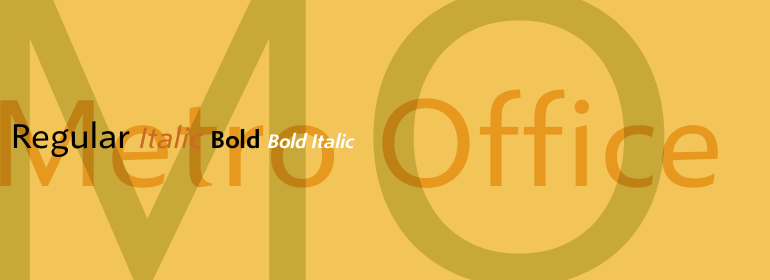
Metro® Office
Metro® Office,这款字体结构工整、笔画清晰,兼顾美观与易读性,适用于标题、正文、海报、包装、LOGO 等多种场景。字形优雅稳定,风格百搭耐看,适配日常排版与创意设计,让文字呈现更舒适、更具质感。Metro® Office一笔一画,皆是细节,以均衡的比例、流畅的线条打造舒适视觉体验,字形端正大气,风格简约现代。无论是商业设计、品牌宣传还是日常排版,都能轻松驾驭,让文字更有格调与力量。Metro® Office字体下载。
字体品牌: Linotype(Monotype) 设计师:Kobayashi,Akira 字体分类:无衬线体、正文字体 字体属性:外文 字符集:Unicode 发布时间: 2018
每年,越来越多的文本都是直接在办公应用的计算机屏幕上阅读,或者从复印机或激光打印机打印出的纸张上阅读。如今清晰、易读的字体在办公室通信中比以往任何时候都重要。然而,每个员工都希望在公司里有一点个性。大多数办公环境仅配备了几种基本字体,这些字体经过优化可用于文本、激光打印机和屏幕上。
Linotype Office Alliance字体可确保数据清晰度。每个字体家族的所有字体粗细都具有相同的字符尺寸;个别字母或单词的样式可以在不影响自动换行的情况下做改变!所有数字、数学符号和货币符号均为表格形式;它们具有相同的字符设置宽度,从而确保没有什么可以能妨碍图形、图表和表格设计的清晰。除了非常开放和清晰之外,该家族字体中的字符还具有相同的大写字母高度和相同的x高度。Linotype Office Alliance字体适当地简化了财务报告的制作和阅读。
Office Alliance系统中的其他三个家族包括Metro Office,Times Europa Office和Trump Mediaeval Office。
Every year, more and more text is read directly on a computer screen in office applications, or from freshly printed sheets from a copier or laser printer. Clear, legible text faces are more imperative to office communication than ever before. Yet every worker desires a small bit of personality in the corporate world. Most office environments are only equipped with a few basic fonts that are truly optimized for use in text, with laser printers, and on screen.
The Linotype Office Alliance fonts guarantee data clarity. All of the font weights within the individual family have the same character measurements; individual letters or words may have their styles changed without line wrap being affected! All numbers, mathematical signs, and currency symbols are tabular; they share the same set character width, ensuring that nothing stands in the way of clear graph, chart, and table design. In addition to being extremely open and legible, the characters in this collection's fonts also share the same capital letter height and the same x-height. The production and reading of financial reports is duly streamlined with the Linotype Office Alliance fonts.
The Metro Office family is designed after the model of the original sans serif family produced by W.A. Dwiggins and Mergenthaler Linotype's design studio during the late 1920s and 1930s. A distinctly new interpretation of the sans serif idea, Metro was a thoroughly American" sans serif when it was released. However, over the ensuing decades, it became a favorite the world over. Moreover, it is one of the first "humanist" sans serif typefaces designed.
While redesigning Metro in 2006, Linotype's Type Director Akira Kobayashi drew from his own knowledge of humanistic letterforms. The result is a redefined Metro; a typeface that is finally ready for heavy text setting. The original Linotype Metro never had italic variants. Kobayashi has created oblique variants, extending its use in document setting. A double-storey a and g, as well as a wider w were features of Dwiggins' original Metro design that were filtered out by Mergenthaler Linotype in the 1930s. Kobayashi remedied this historical slight, retooling Dwiggins' original forms and optimizing their legibility. Kobayashi has additionally retooled some of Metro's more troublesome letters, which has black elements that became too dense. By opening up the troublesome joins (like that on the Q), Kobayashi has given his new Metro a more even color in text, improving its legibility while retaining its original spirit.
The other three families in the Office Alliance type system include Neuzeit Office, Times Europa Office, and Trump Mediaeval Office."